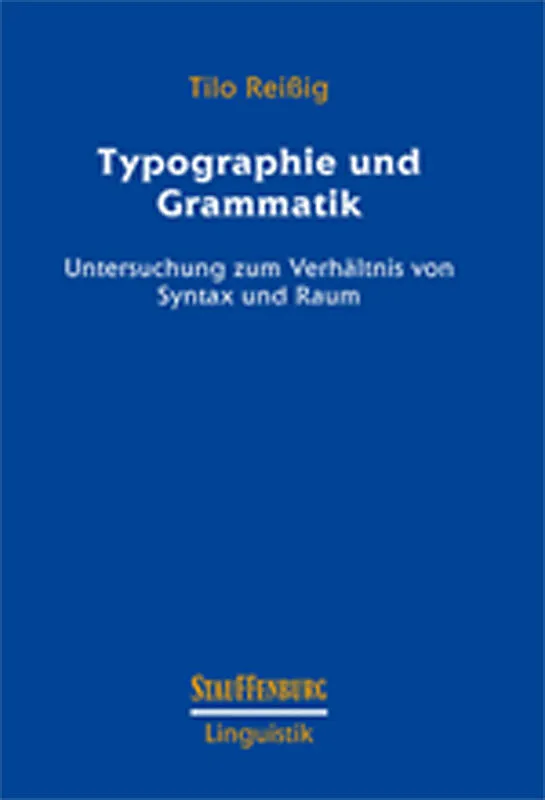
Typographie und Grammatik
Schriftsprachliche Zeichen unterliegen in ihrer Realisierung immer typographischer Gestaltung. Zum einen umfasst die typographische Gestaltung eines Textes die materielle Gestalt der Zeichen, zum anderen die räumliche Anordnung dieser Zeichen. Dass die materie...